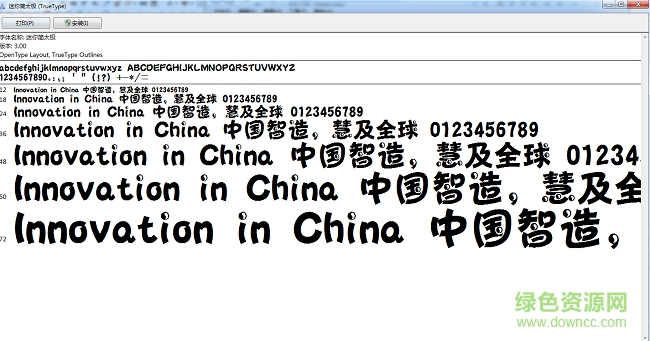
Jtaiji是什么字體?jtaiji字體是一款ttf格式的迷你簡太極藝術(shù)字體,張弛有度,圓潤大方,每一個點都是黑白相間的太極符號,非常特別,適合朋友們在進行廣告海報等詞面設(shè)計的時候使用,即有亮點又突出,喜歡的小伙伴趕緊下載收藏吧!
迷你簡太極字體是一款柔中帶剛,又灑脫不羈、隨心所欲,有點兒像舞太極,讓人一看字中蘊含著力道,取了太極剛?cè)岵木A,將舒展優(yōu)美、動作和順、平正樸實的太極文化融入書法當中!